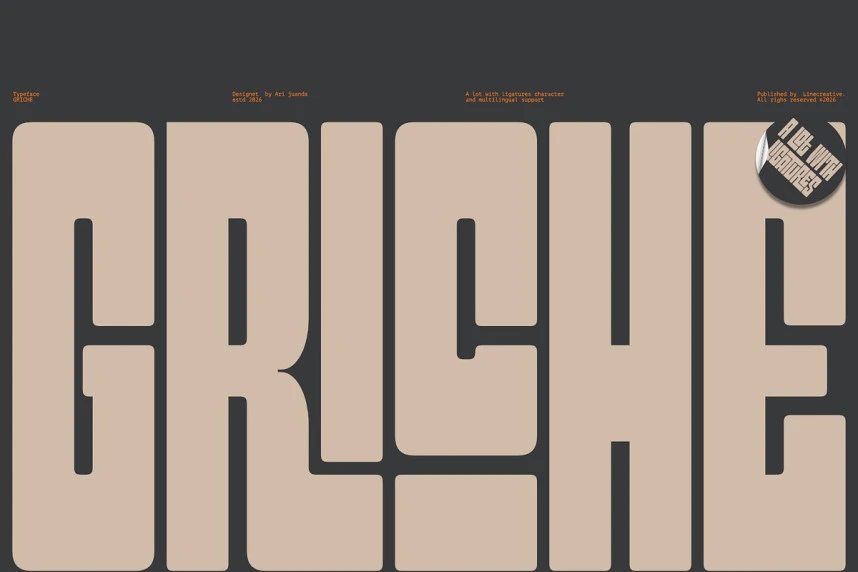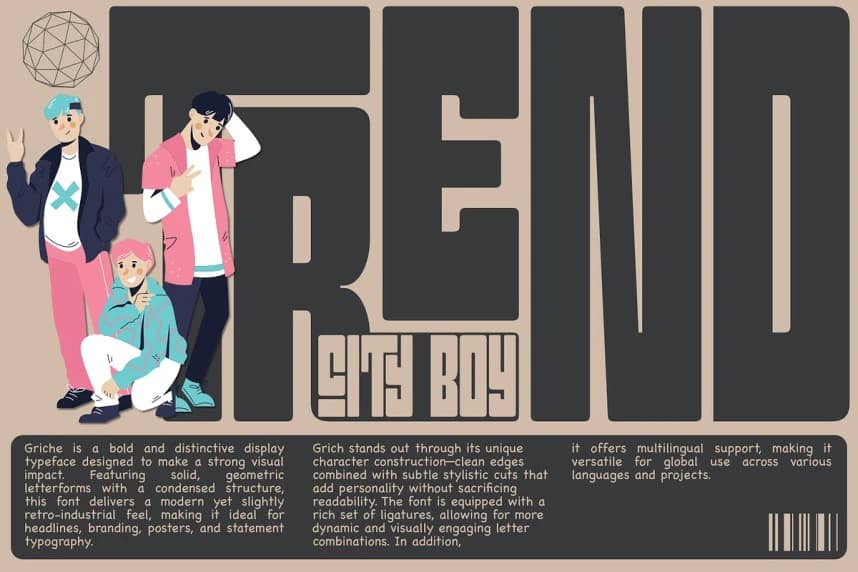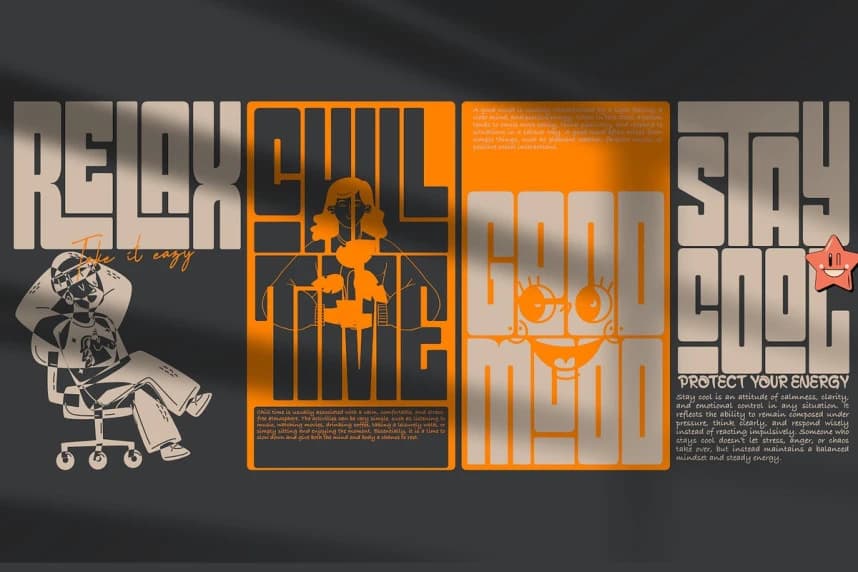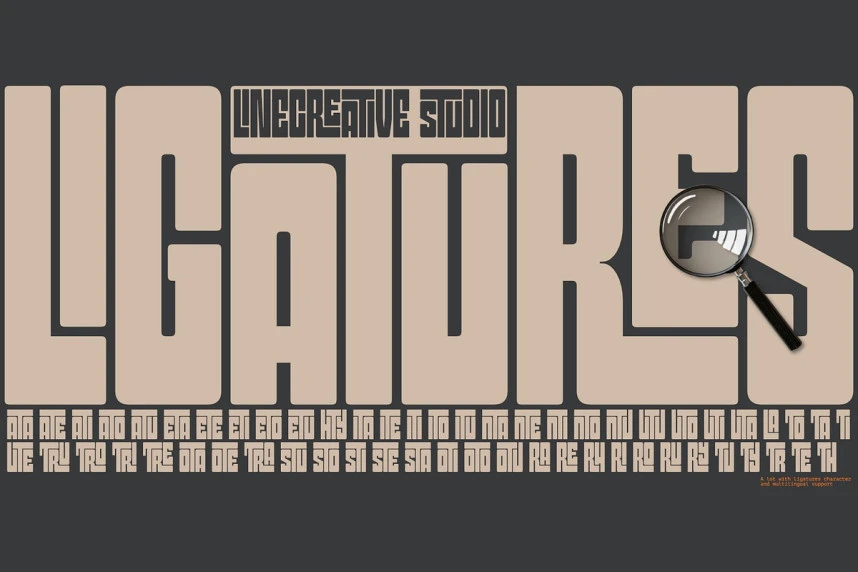
Griche Font
Griche Font, güçlü bir görsel etki yaratmak üzere tasarlanmış cesur ve ayırt edici bir gösteri yazı tipidir. Katı ve geometrik harf biçimlerine sahip yoğunlaştırılmış bir yapıya sahip olan bu yazı tipi modern bir hissi verir ve aynı zamanda biraz retro-endüstriyel bir hava katar; bu nedenle başlıkla
Griche Font, güçlü ve ayırt edici bir başlık yazı tipi olarak tasarlanmıştır ve etkileyici bir görsel etki yaratmayı amaçlar. Katı, geometrik harf biçimlerine sıkıştırılmış bir yapıya sahip olan bu yazı tipi, modern bir hissi ile hafif retro-endüstriyel bir hava verir ve bu da onu başlıklar, marka kimliği, afişler ve ifade tipografisi için ideal kılar.